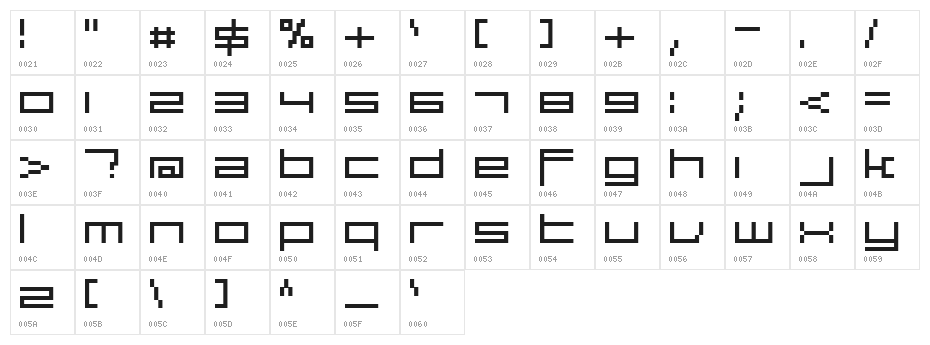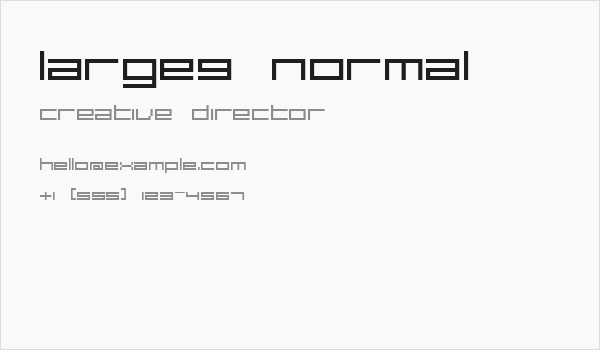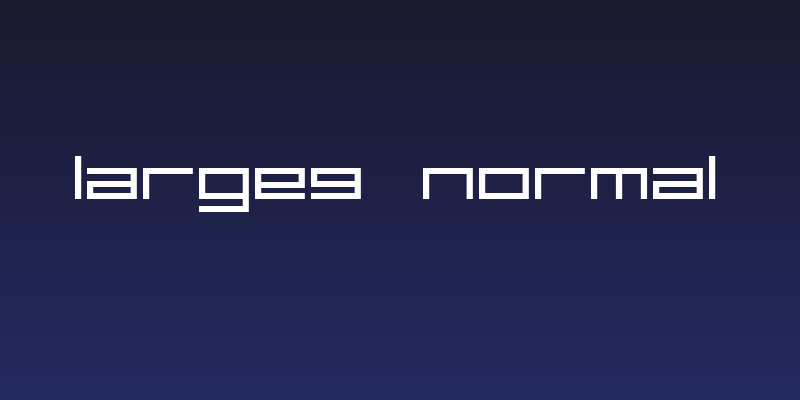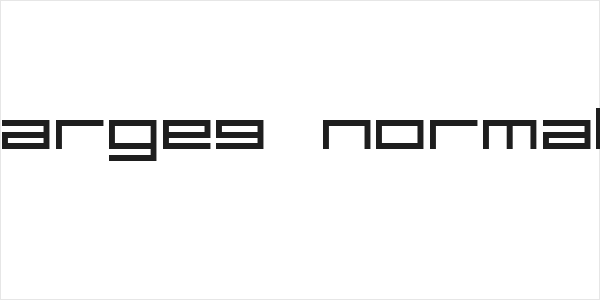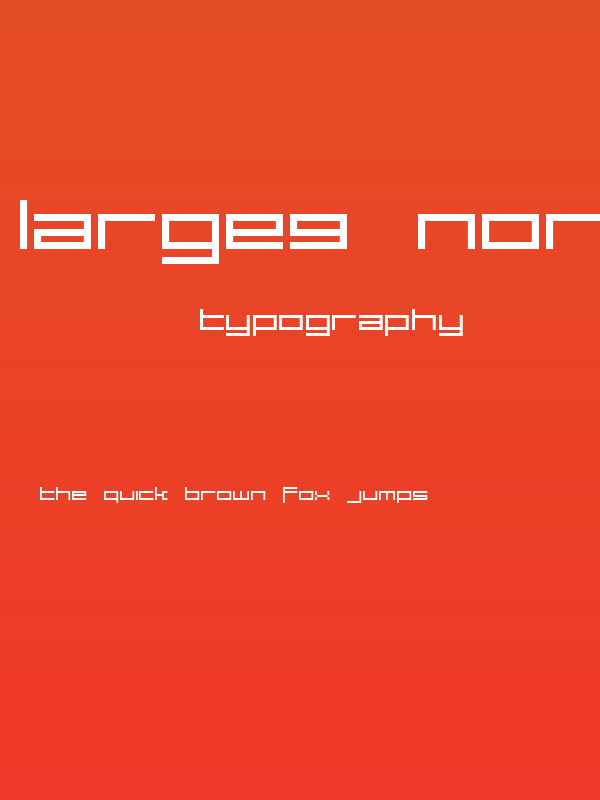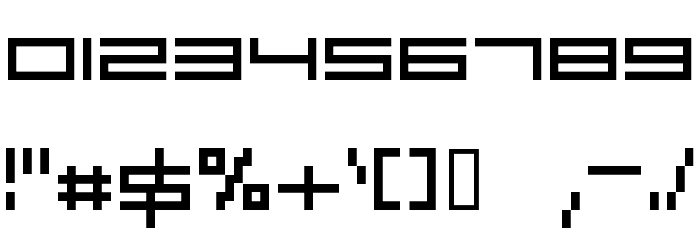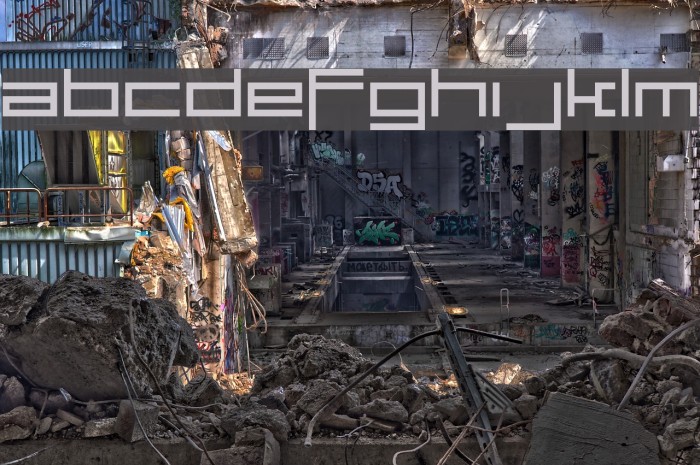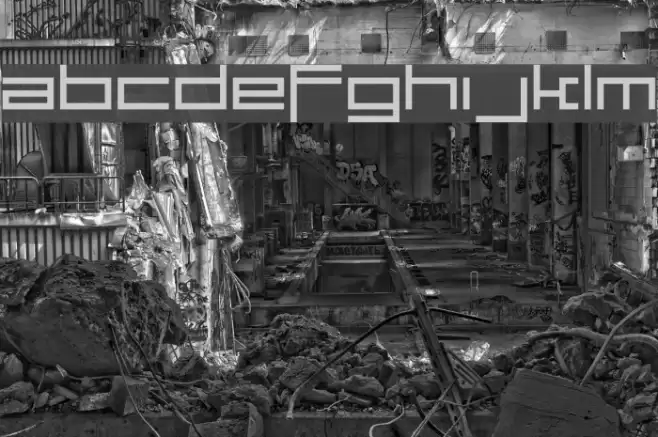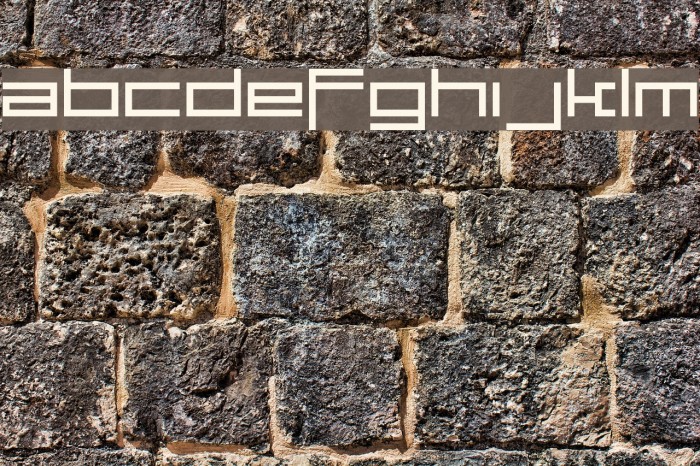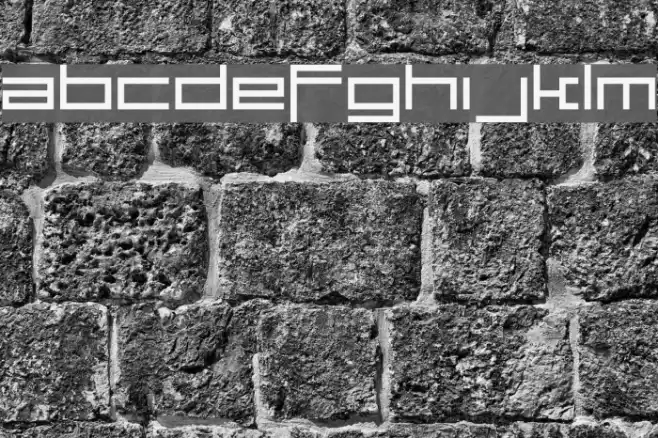
large9 Normal Font
✎ Pixel
| Область применения | Headlines, Digital displays, Coding |
| Рекомендуемые проекты | Ideal for coding environments, digital displays, technical manuals, and futuristic design projects. |